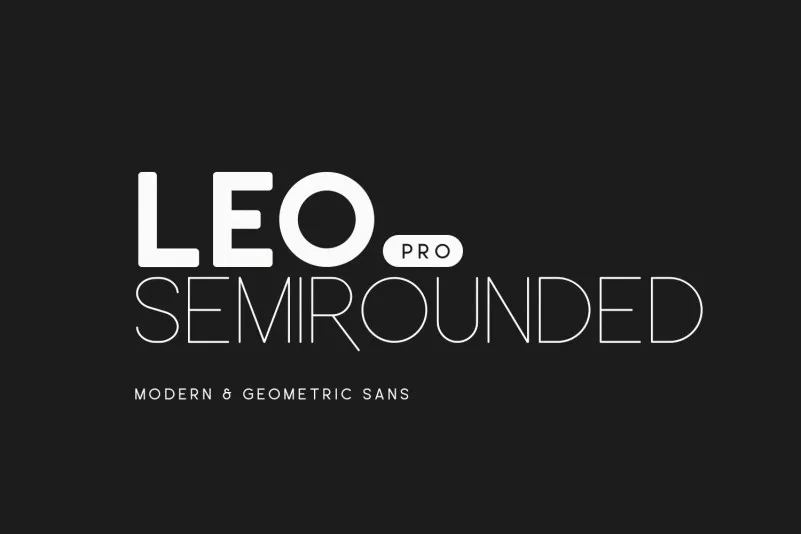
Leo Semi Rounded Pro Font – Download Grátis
A fonte Leo Semi Rounded Pro é uma evolução do famoso sistema de escrita Leo Sans, criado por onedollarfont. Composta por 10 pesos diferentes, esta moderna sans serif apresenta um toque geométrico e cantos semi-redondos que prometem oferecer grande diversidade para os designers gráficos. Este segundo lançamento da família de fontes Leo Sans é projetado para atender a uma variedade de necessidades, como design gráfico, sinalização corporativa ou design editorial. Além disso, possui opções de suporte linguístico ampliado e símbolos monetários, tornando-o altamente versátil e adequado para qualquer aplicação que exija um estilo moderno e elegante. Leo Semi Rounded Pro é perfeito para aqueles buscando uma fonte gráfica sofisticada, com opções de uso em diferentes formatos, seja digital, comercial ou para fins editoriais.